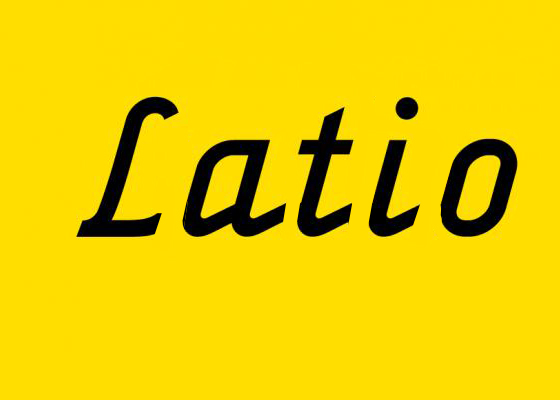
Font / Alternative gesucht
Ich suche die Schrift die für dieses "Logo" verwendet wurde. Meint Ihr das ist eine eigens für dieses Unternehmen erstellte Font?
Ich dächte diese Schrift schon woanders gesehen zu haben.
Das Junghans Logo geht wirklich in diese Richtung. Es wurde denke ich um die 1950 genutzt. Ist es möglich von dieser Schrift den Designer ausfindig zu machen? Weclhe Font ebenfalls in diese Richtung geht ist die von "Jura Kaffeemaschinen"...
Also wenn der Jura-Schriftzug in deinen Augen in die gleiche Richtung geht, dann suchst du eine Retro-Script und da gibts echt tausende: https://www.myfonts.com/search/tag%3Ascript+tag%3Aretro/fonts/ einfach mal durchscrollen ...
eventuell gefällt dir ja diese:
https://www.myfonts.com/fonts/kyle-wayne-benson/millie/
oder diese:
https://www.myfonts.com/fonts/kyle-wayne-benson/benson-script/
oder diese:
http://www.houseind.com/fonts/bullet
Leider habe ich bei noch keiner dieser Schriften das "Formelle" gefunden was die Junghans oder Latio Schrift hat. Die Schriften gehen meist in die "Schreibschhriften" hinein und haben ähnliche Konturen aber doch fehlt Ihnen was. Bringt es jetzt noch etwas weiter zu suchen?
Habe noch einen Linotype Experten hinzu gezogen und warte da auf ein Feedback. Fällt euch noch irgend etwas ein?
Ich sehe schon, ihr seit auf dem richtigen weg :-)
Habt ihr noch irgend welche Hinweise denen ich nachgehen könnte?
Oh weh, sollte ich die dann zu meiner Sommerloch-Schrift küren??? "Latio-Junghans"?
Habt ihr noch irgend welche Hinweise denen ich nachgehen könnte?
ja, du könntest liva grinberga eine mail schicken. die hat offenbar an dem rebranding (mit)gearbeitet und müsste demnach wissen, ob der schriftzug auf einer existierenden schriftart basiert bzw. ob es noch andere vorbilder – außer dem alten, aus der zapf chancery abgeleiteten schriftzug – gibt. wenn du was von ihr hörst, dann lass es uns auch wissen.